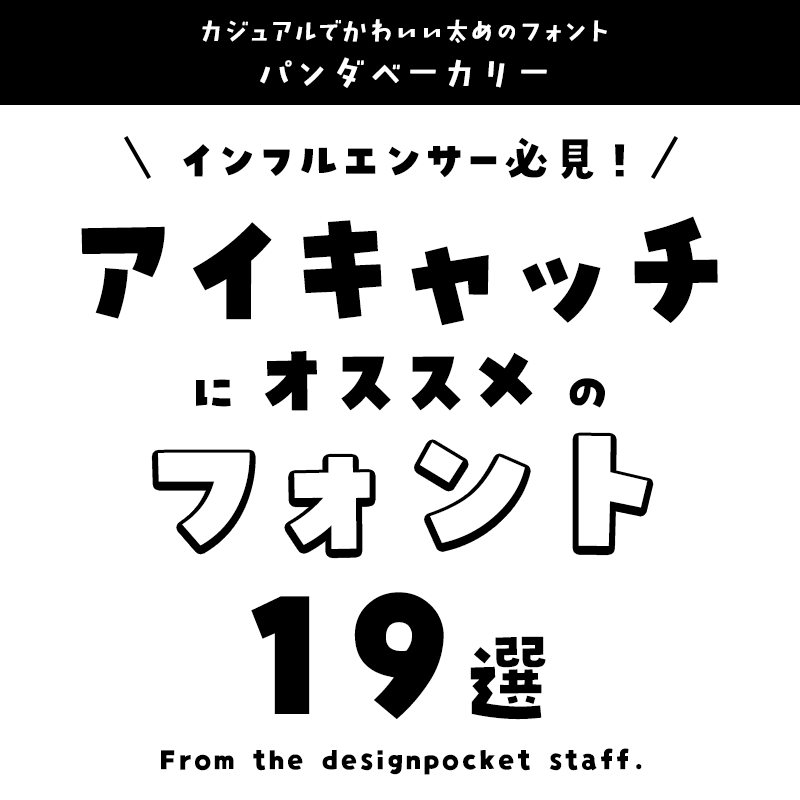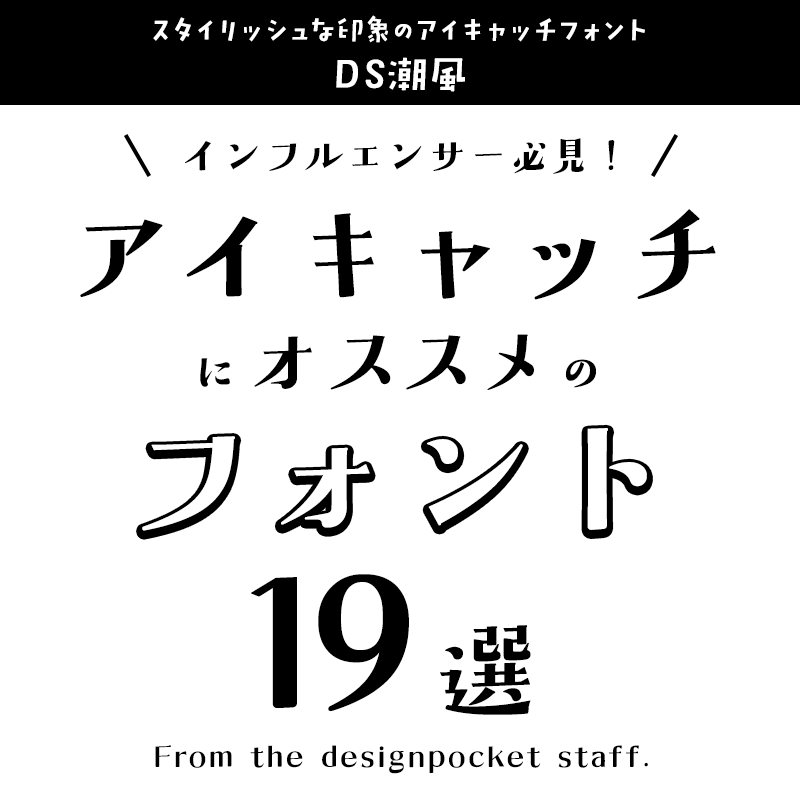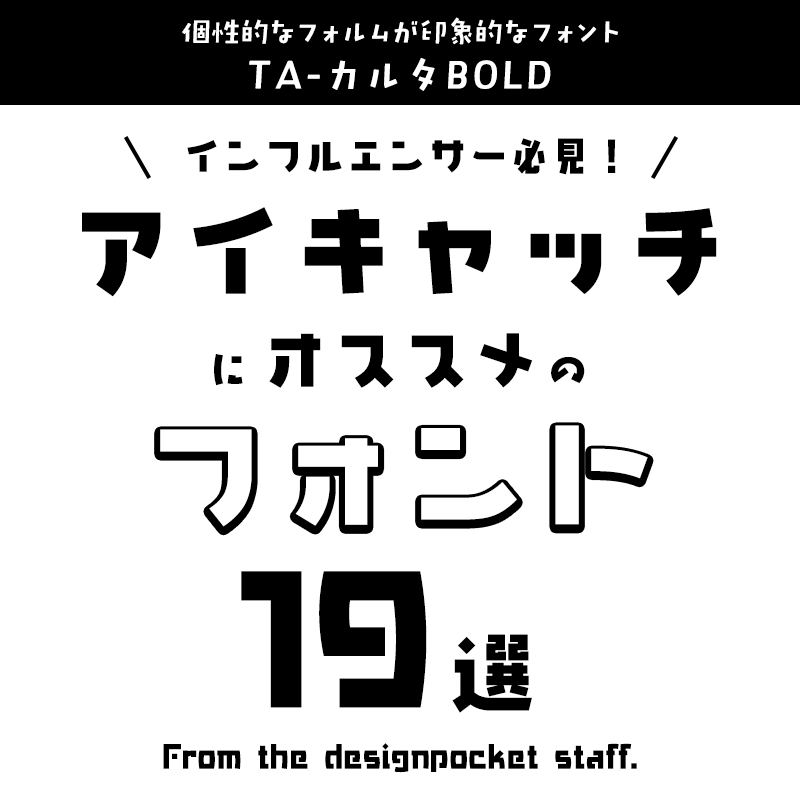
アイキャッチに合うフォント:特化型 目的別フォントガイド #065
今回はアイキャッチに合うフォント。日々フォントのことばかり考えている当店スタッフが直感的に選んだフォントをご紹介します。
アイキャッチに合うフォントをスタッフが選びました
アイキャッチに合うフォント エヌユー太角ゴシック
視認性の高い太目のアイキャッチフォント
エヌユー太角ゴシック【CFONT】
アイキャッチに合うフォント エヌユー太角ゴシック
どっしりとした男前のフォントをイメージして、ひらがな・カタカナは少しポップなフォルムにデザインしました。
アイキャッチに合うフォント パンダベーカリー
カジュアルでかわいい太めのフォント
パンダベーカリー【鈴木メモ】
アイキャッチに合うフォント パンダベーカリー
手描きのリズムを活かした、カジュアルで太めのかわいいフォントは、スイーツや子供向けにピッタリです。
アイキャッチに合うフォント DS潮風
スタイリッシュな印象のアイキャッチフォント
DS潮風【七種泰史/デザインシグナル】
アイキャッチに合うフォント DS潮風
明朝体に近い太めの縦画、角ばったウロコ、たっぷりの墨汁で筆を走らせたようなハネが特徴。波の音、風の音。波しぶき、潮の香り。波打ち際での自然の風をイメージした書体です。
アイキャッチに合うフォント DSあかり
シンプルな印象のアイキャッチフォント
DSあかり【七種泰史/デザインシグナル】
アイキャッチに合うフォント DSあかり
タイトル・見出しフォントとしても本文フォントとしても使える、汎用性の高いフォント。どんなデザインに配置しても馴染む適度な太さ。角ばった律儀なフォルムと、明るく軽やかな雰囲気を両立させたフォントです。
アイキャッチに合うフォント DSきりぎりす
楽しい印象のアイキャッチフォント
DSきりぎりす【七種泰史/デザインシグナル】
アイキャッチに合うフォント DSきりぎりす
トリスのハイボールでもおなじみ、切り文字のような大胆さを持った、デザインシグナルの一番人気フォント。
アイキャッチに合うフォント TA-カルタBOLD
個性的なフォルムが印象的なフォント
TA-カルタBOLD【FONT1000】
アイキャッチに合うフォント TA-カルタBOLD
個性的なフォルムのデザインフォントながらもしっかりした太さがあり見る人を惹きつけます!
アイキャッチに合うフォント 花とちょうちょ
メッセージ性の強いアイキャッチフォント
花とちょうちょ【鈴木メモ】
アイキャッチに合うフォント 花とちょうちょ
ペンで右上がりに書いた手書き文字から作った、ちょうちょのように軽やかな日本語フォントです。写真やイラストに書き込みをしたように傾けたレイアウトで使用するのもおすすめです。
アイキャッチに合うフォント 横丁&鍛所 ファイトフォント
勢いのあるアイキャッチフォント
横丁&鍛所 ファイトフォント【六葉情報】
アイキャッチに合うフォント 横丁&鍛所 ファイトフォント
勢いのあるはらいが特徴的な極太の毛筆書体で、荒々しく力強い印象を持っています。タイトルや見出し、ロゴなどにおすすめです。
アイキャッチに合うフォント ティラノゴチ
アクティブな印象のアイキャッチフォント
ティラノゴチ【ヤマナカデザインワークス】
アイキャッチに合うフォント ティラノゴチ
「ティラノゴチ」は手書き文字をベースとして、やんちゃ小僧をコンセプトに作った元気系日本語フォントです。見出しやタイトル、ロゴなどにインパクトを持たせたいとき、力強く元気な印象を持たせたいときに是非お使いください。
アイキャッチに合うフォント こまどり+
ほっこりとした印象のアイキャッチフォント
こまどり+【ヤマナカデザインワークス】
アイキャッチに合うフォント こまどり+
こまどりは小さくかわいい小鳥のイメージで作成した日本語フォントです。ちょっとした言葉や見出しなどに使っていただくと、紙面がカワイイ雰囲気になります。
アイキャッチに合うフォント バサころ書体
親しみやすさのあるアイキャッチフォント
バサころ書体【昭和書体/コーエーサインワークス】
アイキャッチに合うフォント バサころ書体
かすれのあるゴロっとした筆文字で 温かみや親しみやすさを感じられるフォントです。
アイキャッチに合うフォント モトヤ刀筆6 LiteN
力強い印象のアイキャッチフォント
モトヤ刀筆6 LiteN【モトヤフォントlite】
アイキャッチに合うフォント モトヤ刀筆6 LiteN
「爨宝子碑(さんぽうしひ)」という書の古典を基に制作され、ゴシック体の骨格に刀をイメージしたアクセントを付与し、鋭さや躍動感、伝統的な品格を表現した書体です。
アイキャッチに合うフォント モトヤステンシルアポロ6 LiteN
スマートな印象のアイキャッチフォント
モトヤステンシルアポロ6 LiteN【モトヤフォントlite】
アイキャッチに合うフォント モトヤステンシルアポロ6 LiteN
モトヤアポロの清涼感を残しつつ、ステンシル(図柄や模様等をくりぬいた型紙を用いて行う手法)処理を施した書体です。
実況プレイに合うフォント AR明朝体U
誠実な印象のアイキャッチフォント
AR明朝体U【アーフィック】
実況プレイに合うフォント AR明朝体U
明朝体の中でも見出しに使用できる極太書体です。
アイキャッチに合うフォント AFSセリフゴシック04E
どっしりと落ち着きのあるアイキャッチフォント
AFSセリフゴシック04E【フォントユーコム】
アイキャッチに合うフォント AFSセリフゴシック04E
欧文のエジプシャン書体に近いデザイン。どっしりと足のセリフは腰の据わった安定したデザインで落ち着きや安定感を与えます。キャプションなど短い解説やロゴなどに応用ください。
アイキャッチに合うフォント シーモ太丸ゴシックネオ
やわらかな印象のアイキャッチフォント
シーモ太丸ゴシックネオ【CFONT】
アイキャッチに合うフォント シーモ太丸ゴシックネオ
幾何学的なフォルムをイメージしてデザインされたポップな表情が面白い効果を生む丸ゴシック体ベースのフォント。墨だまりのような丸みも特徴的です。
アイキャッチに合うフォント 筆技名人フォント 遊月体
温もりを感じるアイキャッチフォント
筆技名人フォント 遊月体【ミーネット】
アイキャッチに合うフォント 筆技名人フォント 遊月体
手書きの温もりと子供の頃の懐かしさが甦るクレヨンフォント。クレヨン特有のデコボコ感と際立つ太文字は、インパクトのあるロゴや子供向け商品のタイトルなどに最適です。
アイキャッチに合うフォント DF娥眉明朝体 W7
華やかな印象のアイキャッチフォント
DF娥眉明朝体 W7(がびみんちょうたい)【ダイナフォント】
アイキャッチに合うフォント DF娥眉明朝体 W7
明朝体をベースに開発された書体であり、細長く弧を描いた眉の形をイメージしたストロークから洗練された女性の柔らかさや優しさを表現した明朝体です。